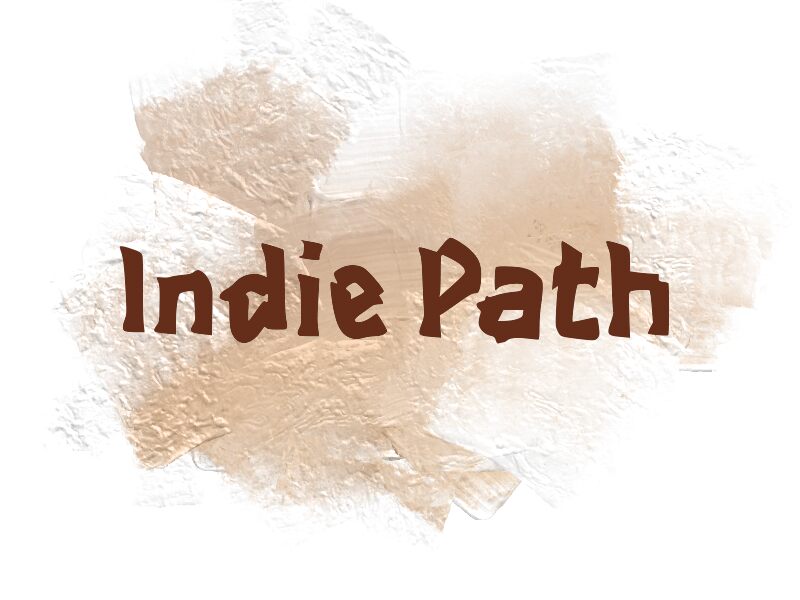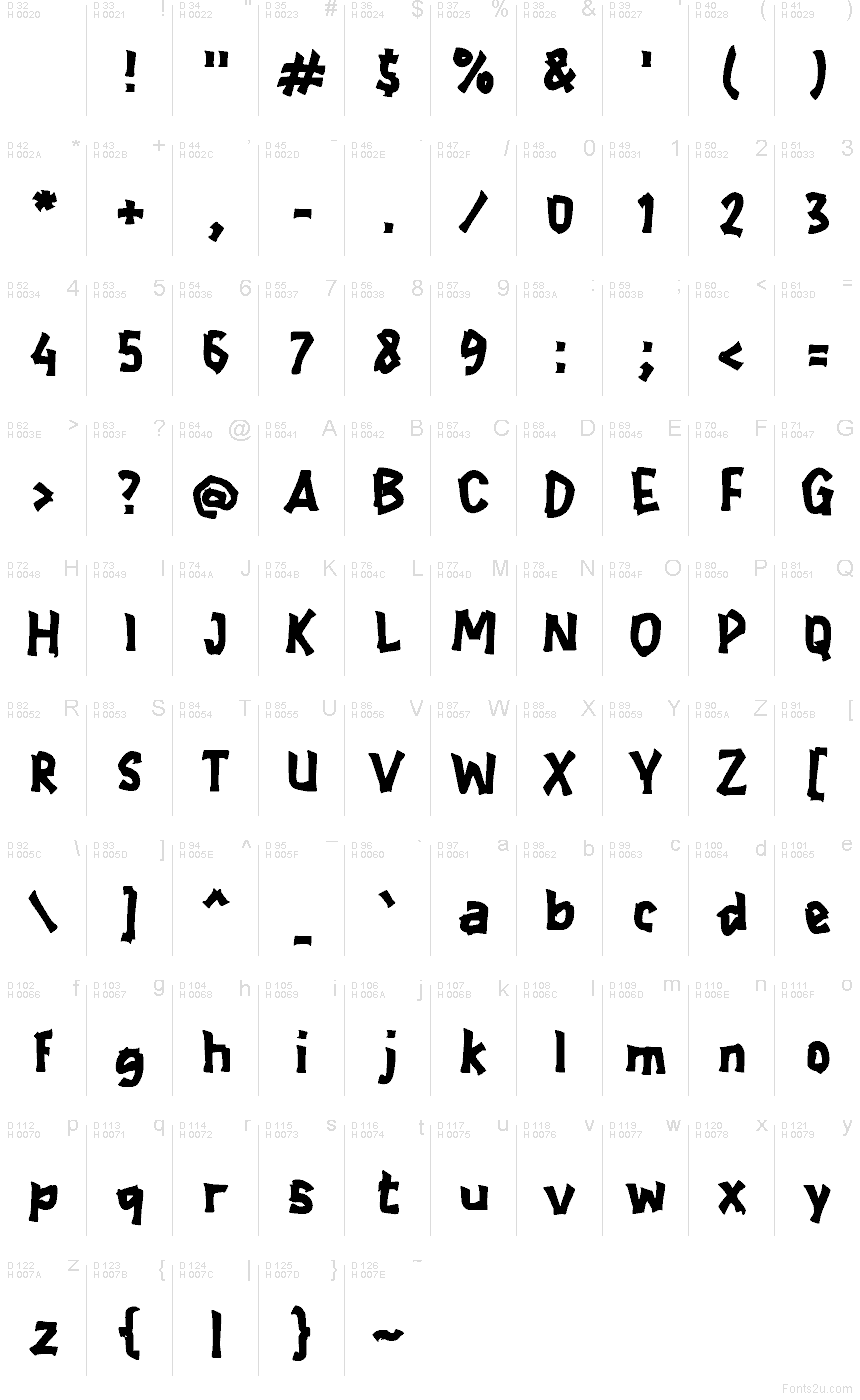
Indie Path od Wep to darmowy, ręcznie wycinany, folkowy krój pisma typu display o swobodnym, niemal bajkowym rytmie. Jego litery przechylają się i chwieją jak wycięte z papieru kształty, łącząc wyraziste krzywizny z ostrymi wcięciami, dzięki czemu cały font sprawia wrażenie zabawnego, rustykalnego i nieco nietuzinkowego.
To sprawia, że naturalnie pasuje do plakatów niezależnych, okładek zinów, identyfikacji kawiarni, ulotek festiwalowych oraz opakowań, które mają brzmieć "domowo". Jako darmowy font, świetnie sprawdza się również w krótkich nagłówkach, planszach tytułowych i logotypach typu badge, gdzie pierwsze skrzypce grają nierówne kontury i żywe sylwetki znaków.
Indie Path